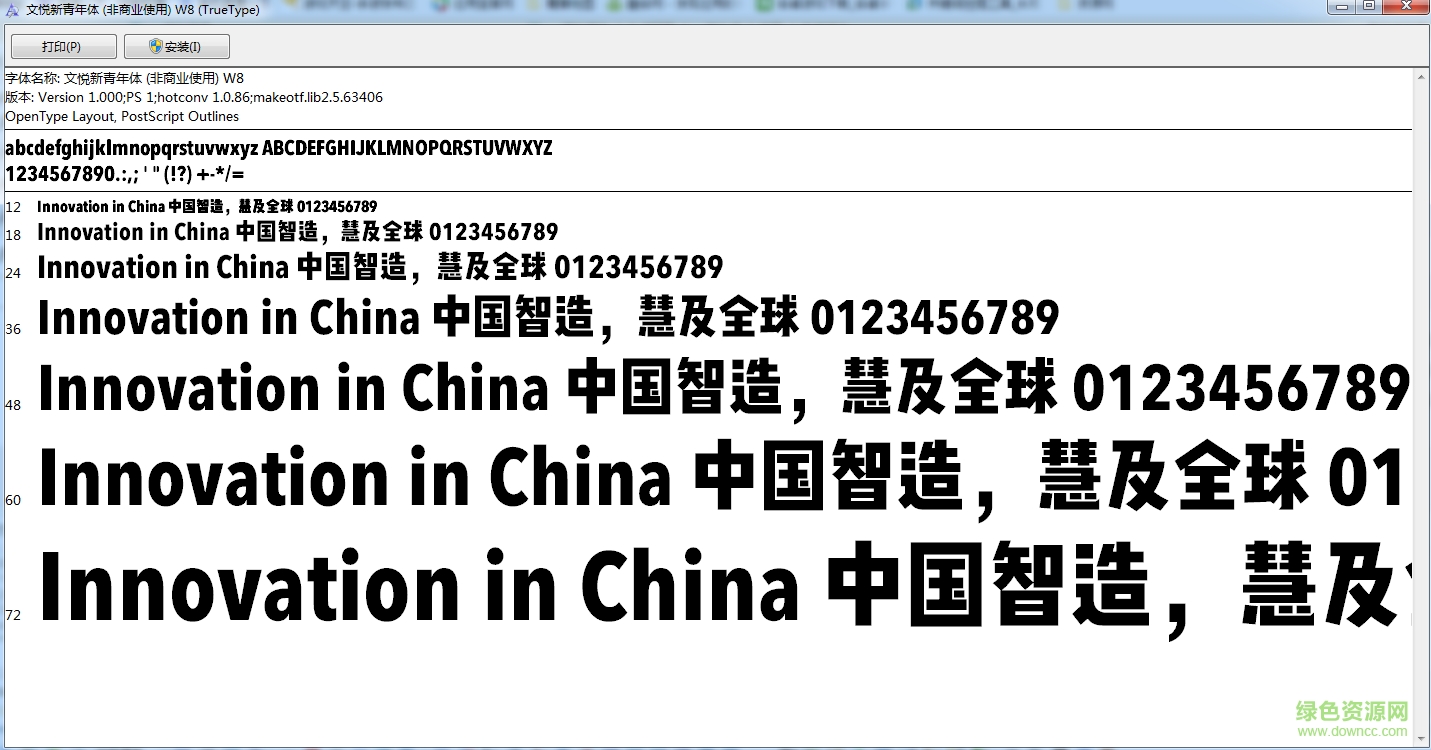
文悅新青年體計(jì)算機(jī)字體,靈感源自二十世紀(jì)的美術(shù)字設(shè)計(jì),結(jié)合了包括創(chuàng)刊于 1915 年的《新青年》雜志書名字標(biāo)的設(shè)計(jì)風(fēng)格。字型上融合新舊兩種元素,將憶古情結(jié)表現(xiàn)得淋漓盡致的同時,又能相得益彰地展現(xiàn)出現(xiàn)今社會所需的極強(qiáng)表現(xiàn)力。
《奇葩說》是一檔由米未傳媒和愛奇藝打造的脫口達(dá)人秀,節(jié)目由馬東主持,并邀請了蔡康永、金星、高曉松擔(dān)任導(dǎo)師,旨在尋找華語世界中,觀點(diǎn)獨(dú)特、口才出眾的最會說話的人。因節(jié)目宗旨與產(chǎn)品氣質(zhì)的奇妙關(guān)聯(lián),2016 年 3 月“文悅新青年體”首發(fā)亮相《奇葩說》第三季。
風(fēng)格復(fù)古并不代表使用場景受限,相反,沉淀百年的爆破力一觸即發(fā)。